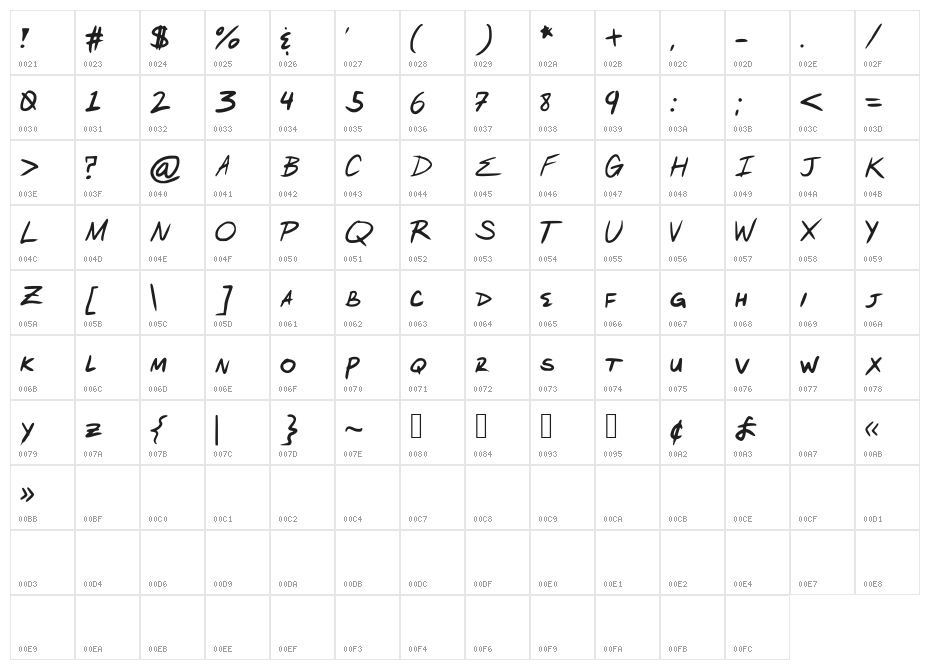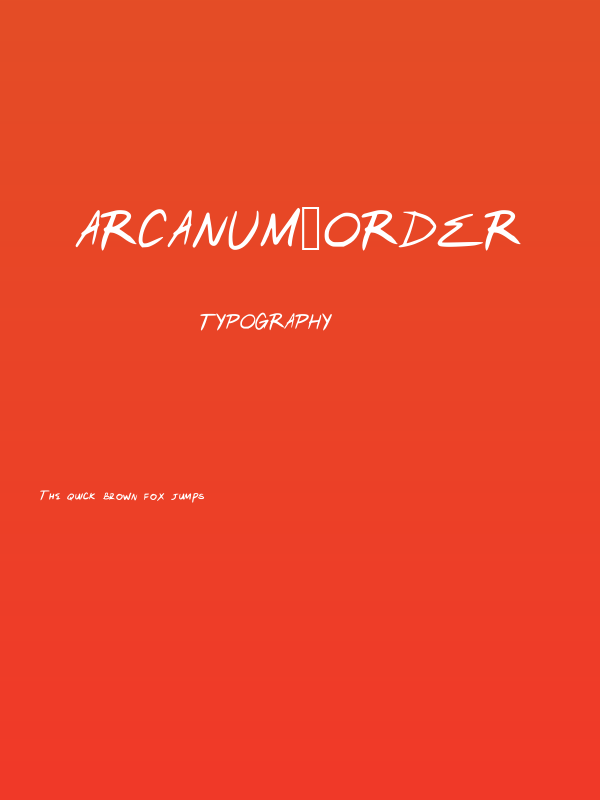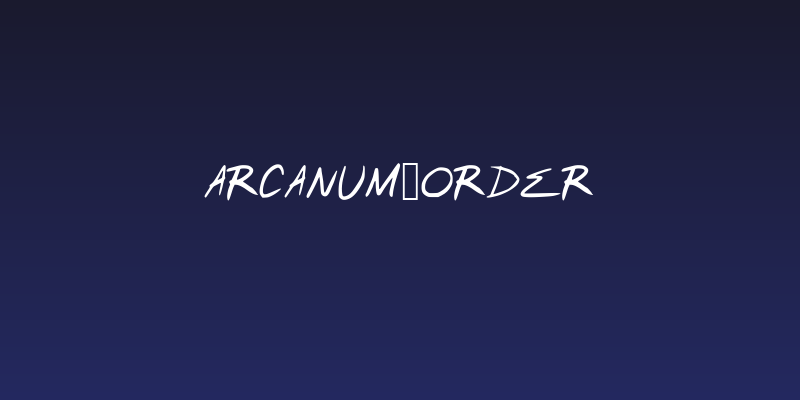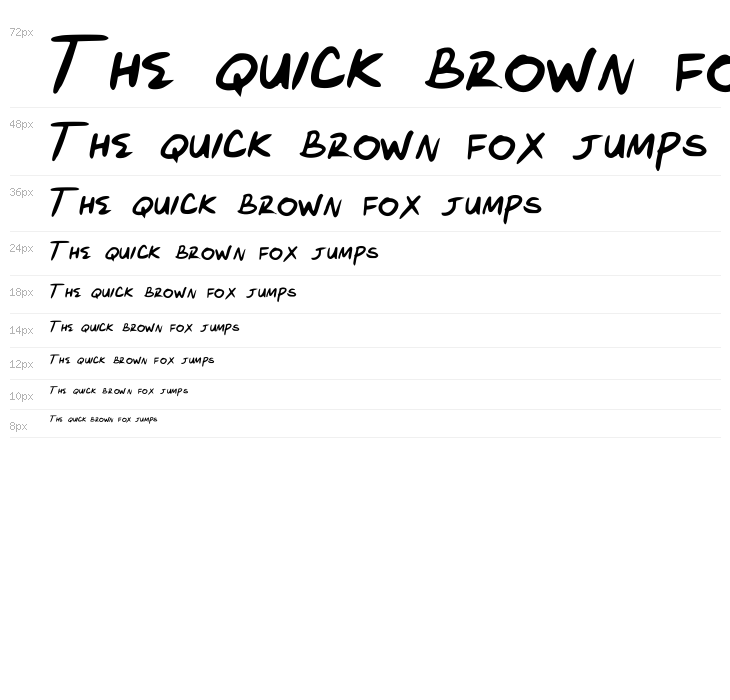
Arcanum_Order Font
| Anwendungsfall | Logos, Headlines, Posters |
| Vorgeschlagene Projekte | Ideal for greeting cards, invitations, posters, and branding projects that aim for a personal and informal touch. |